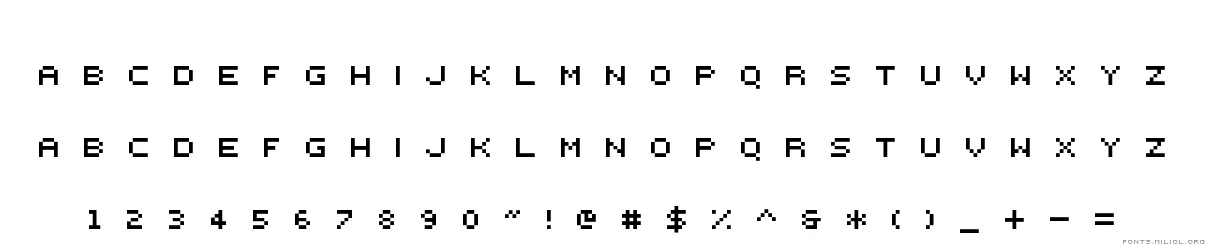
字体名称:000webfont
在网页设计和排版中,字体选择至关重要,而000webfont 作为一款现代感十足的字体,能为设计增添独特的视觉魅力。这款字体线条简洁,适用于标题、LOGO 或强调性文本,能为项目带来专业且时尚的呈现效果。
无论是平面设计还是数字媒体,000webfont 都能提升内容的可读性与美感,是设计师值得收藏的优质字体之一。